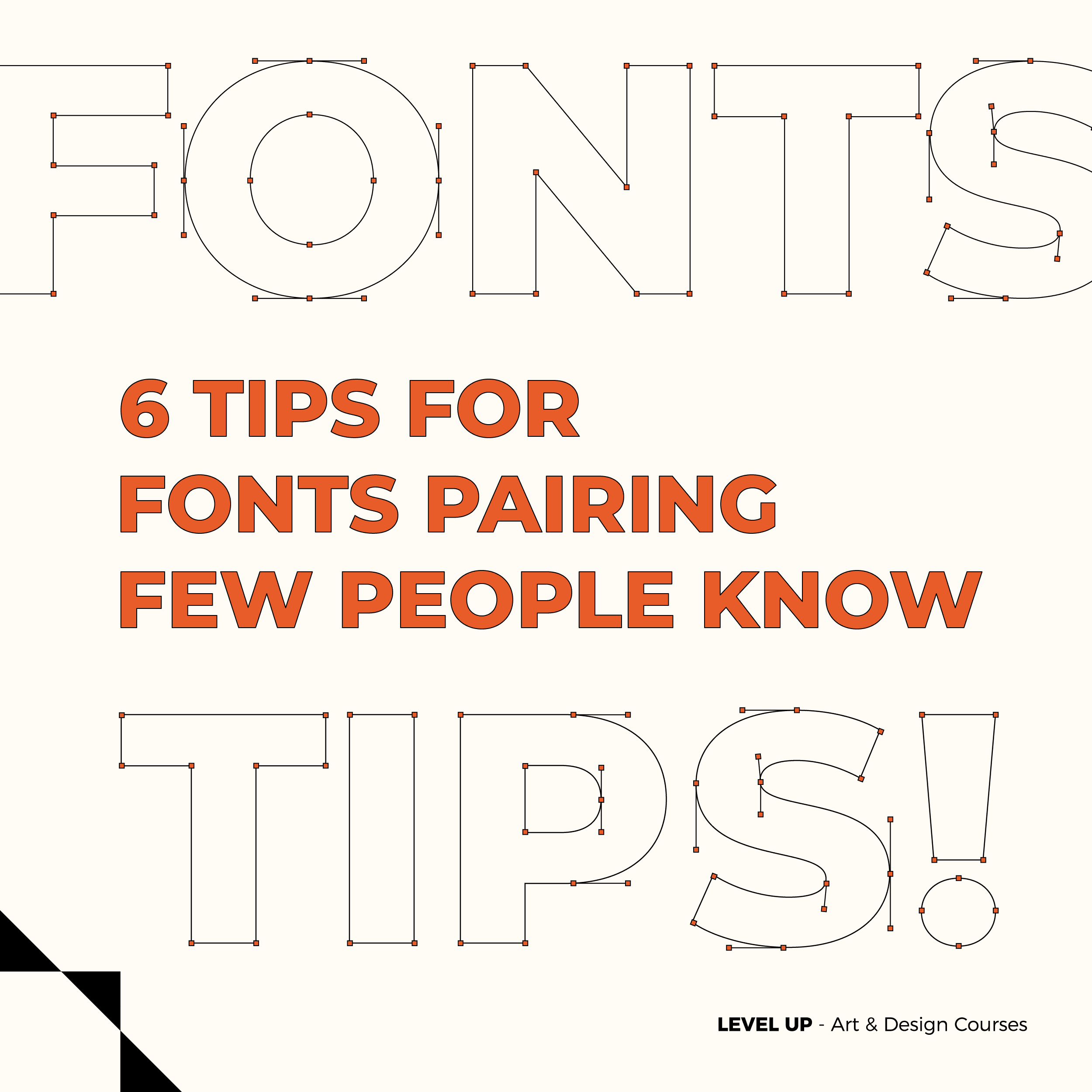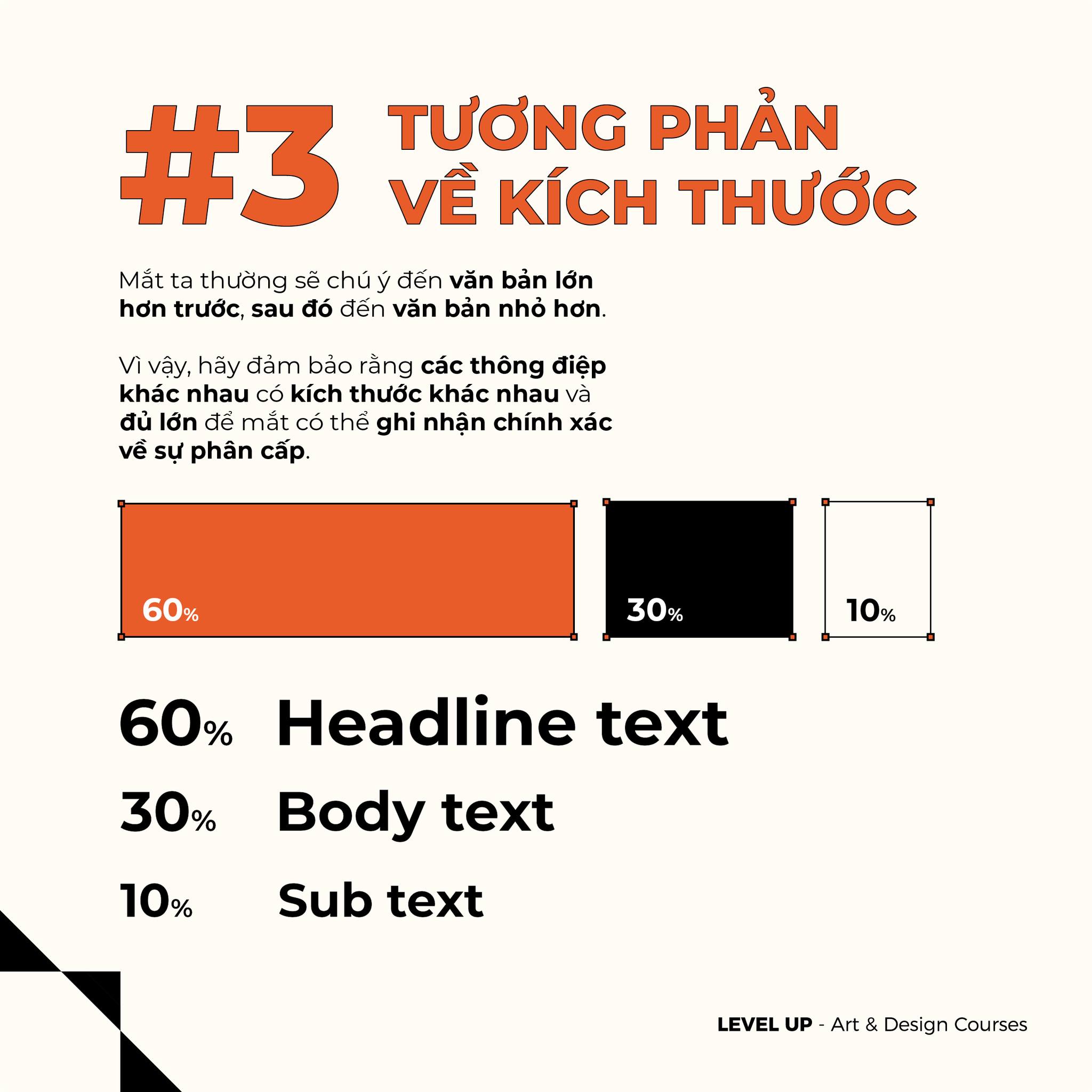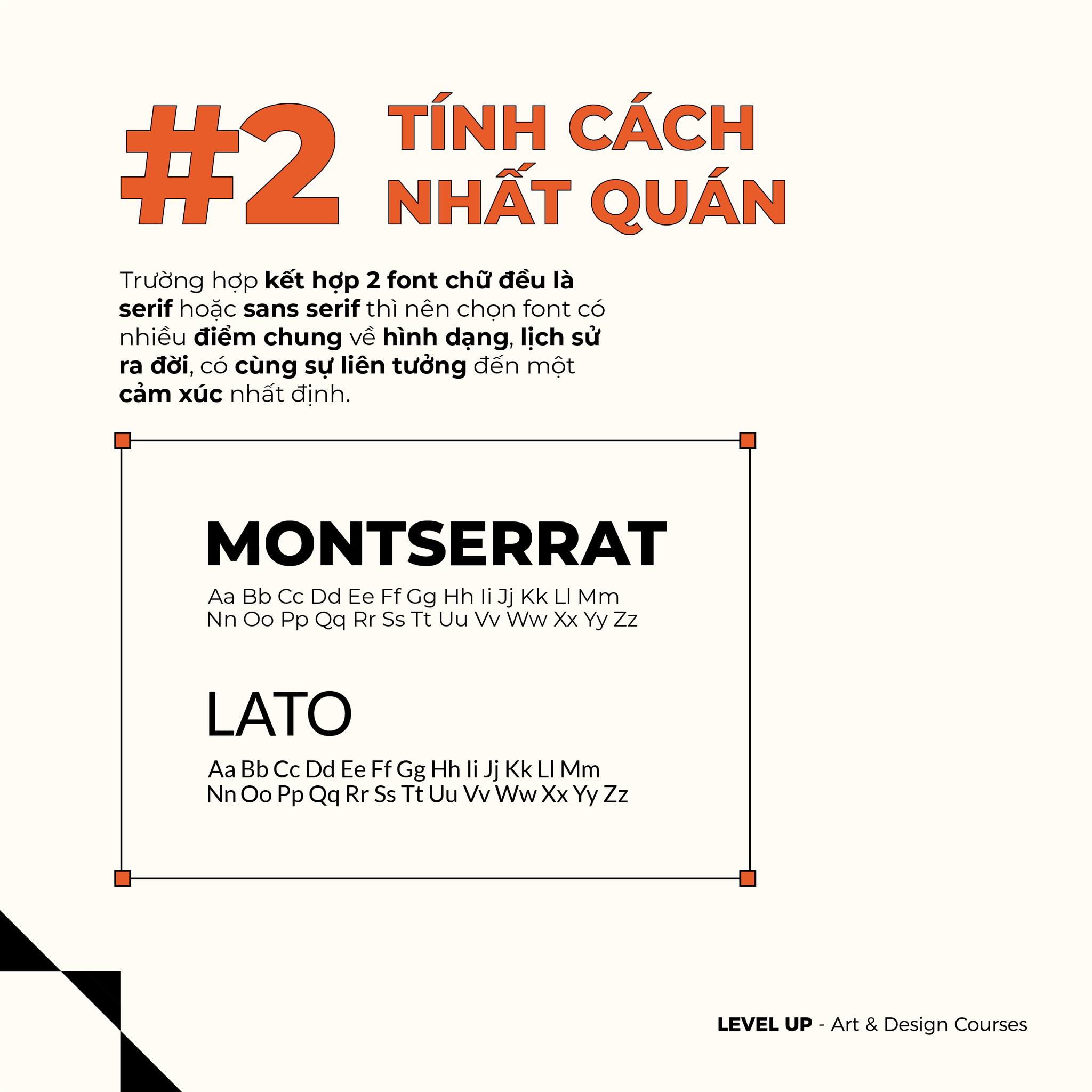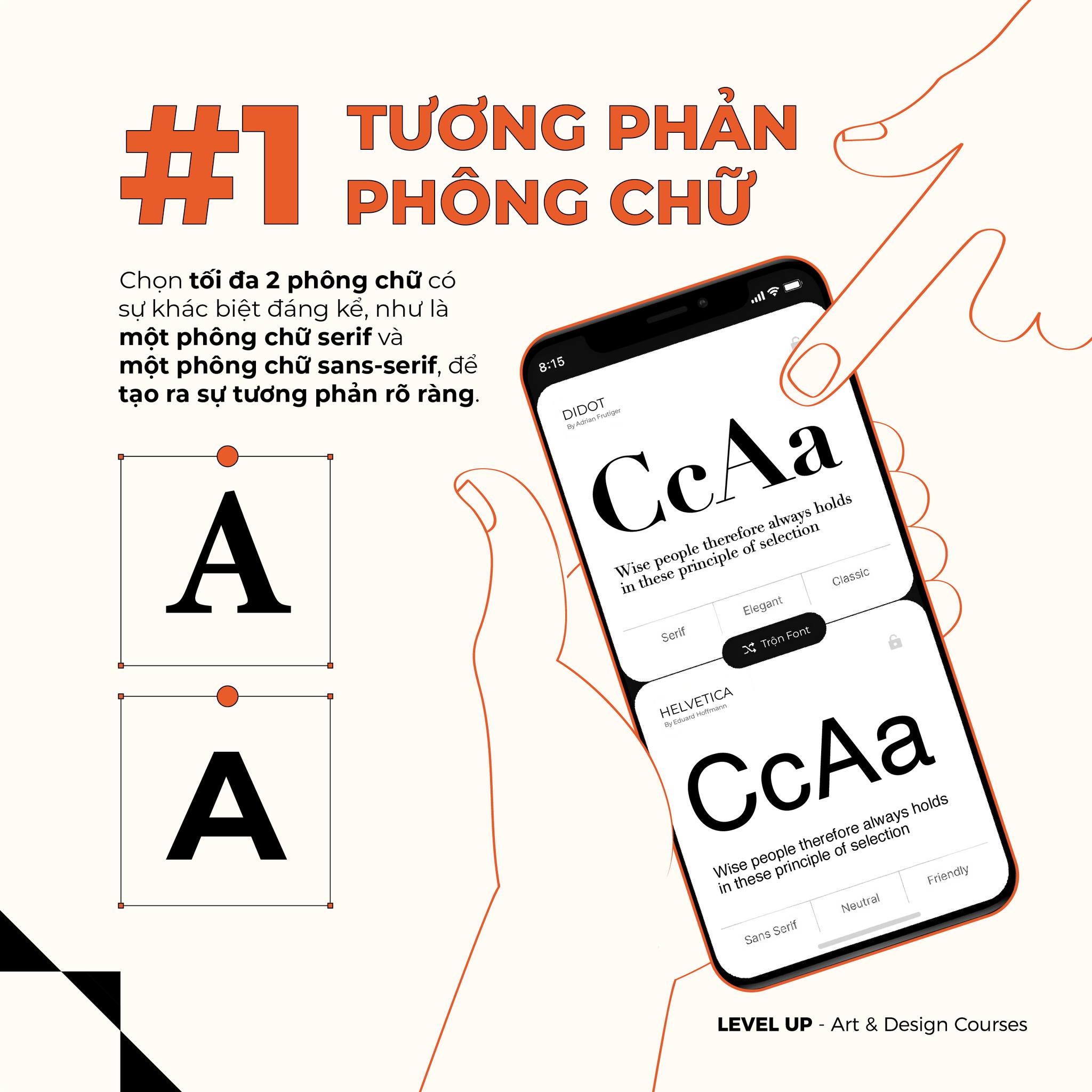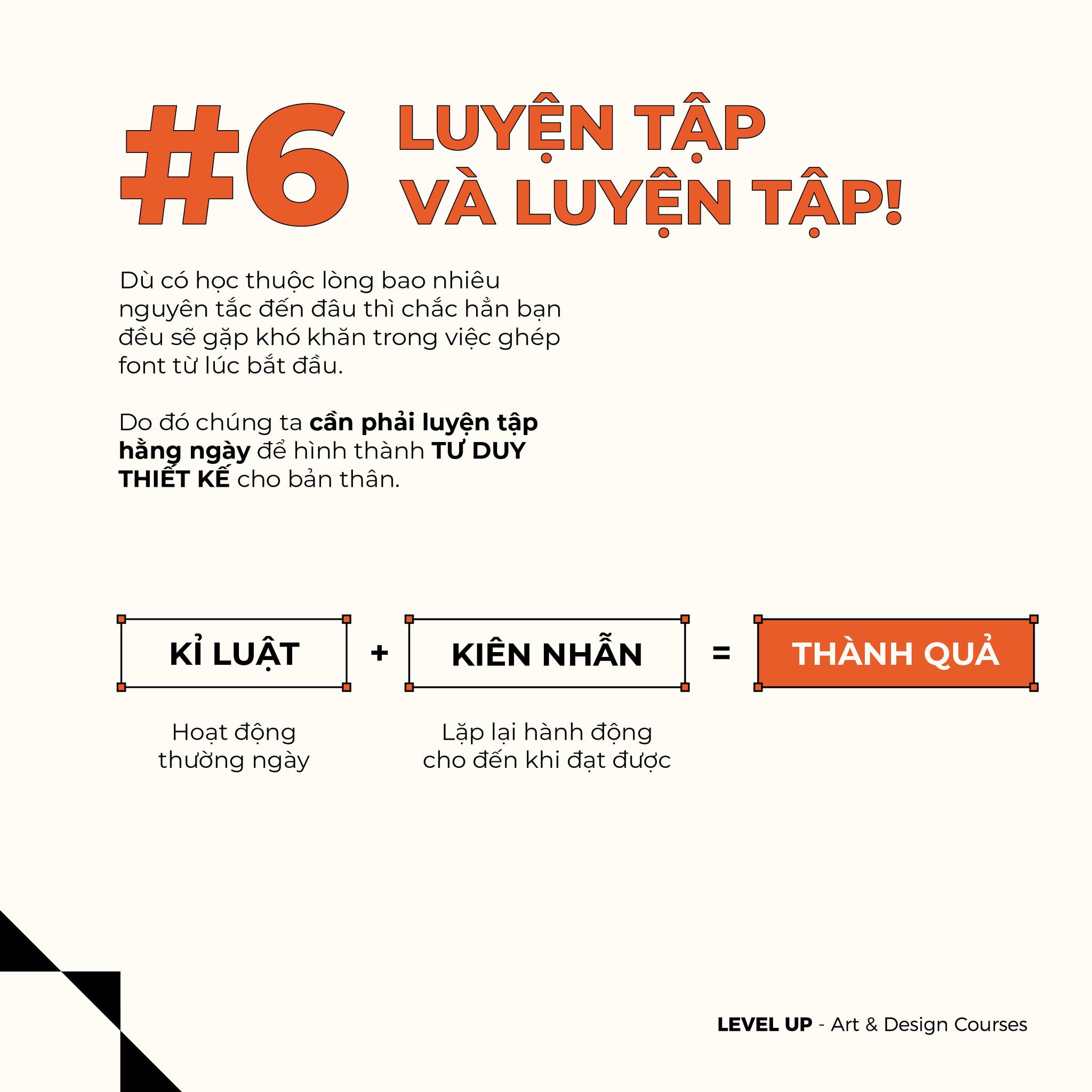
6 tips kết hợp font ít người biết
Việc ghép cặp phông chữ không chỉ là việc chọn hai phông chữ mà bạn thích và sử dụng chúng cùng nhau. Đó là một nghệ thuật đòi hỏi sự hiểu biết về cách các phông chữ tương tác với nhau và làm thế nào để chúng có thể kết hợp một cách hài hòa để tạo ra trải nghiệm thị giác dễ chịu.
Sự kết hợp giữa các phông chữ có thể nâng tầm hoặc phá hỏng một thiết kế. Một sự kết hợp không đúng có thể gây xao nhãng hoặc làm khó hiểu thông điệp mà bạn muốn truyền tải. 6 cách dưới đây sẽ giúp designer dễ dàng hơn trong việc lựa chọn font phù hợp với thiết kế của mình.